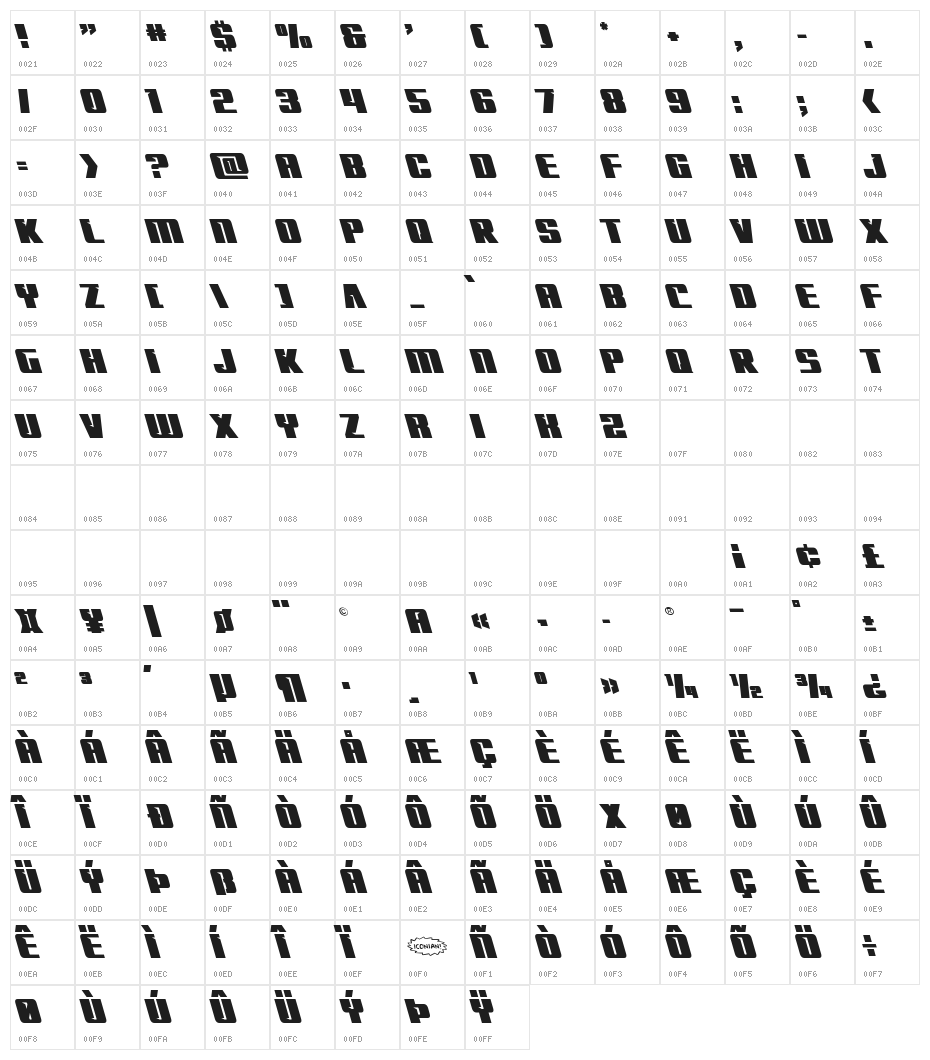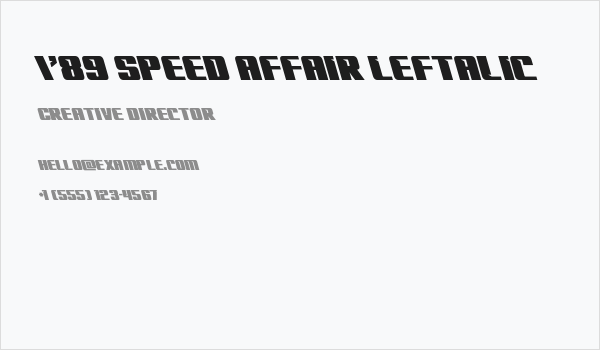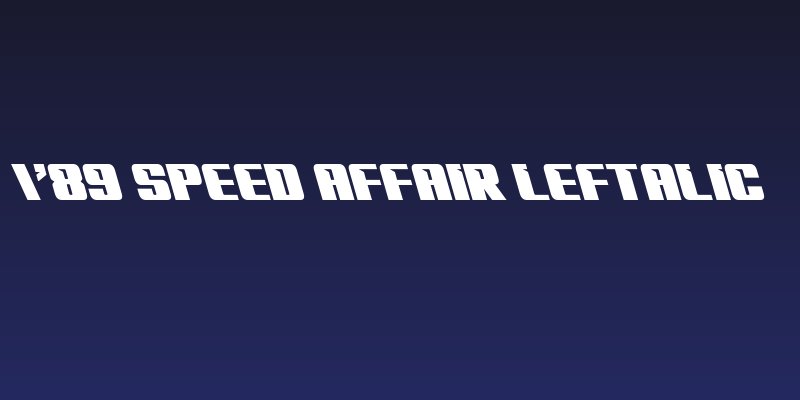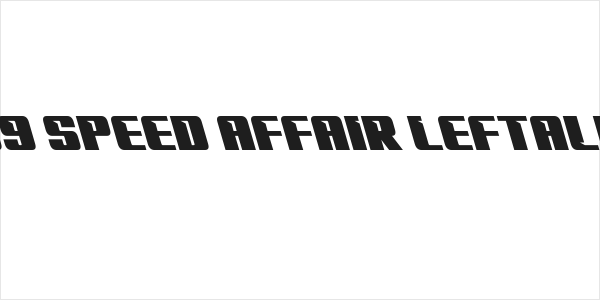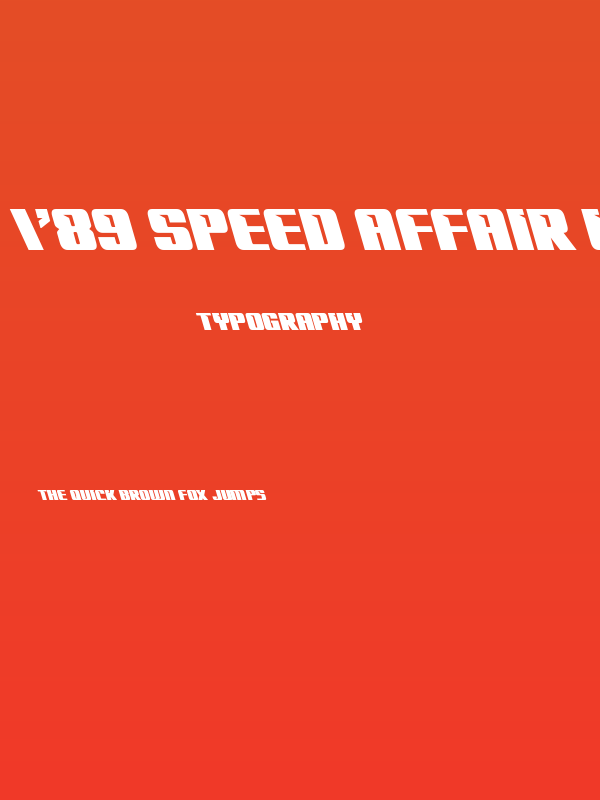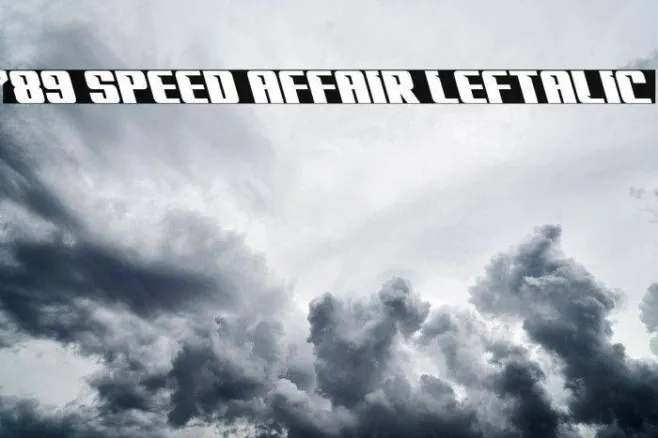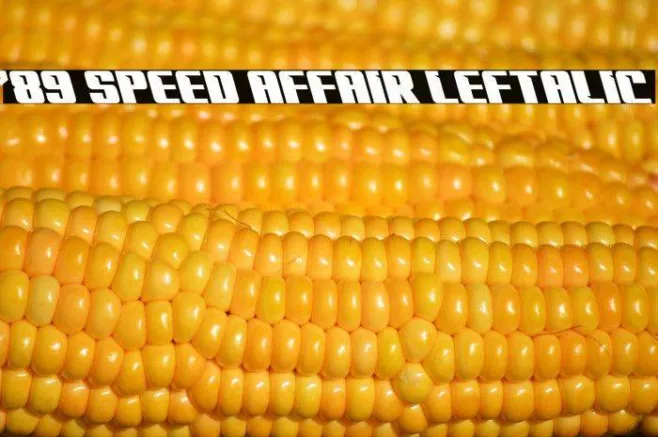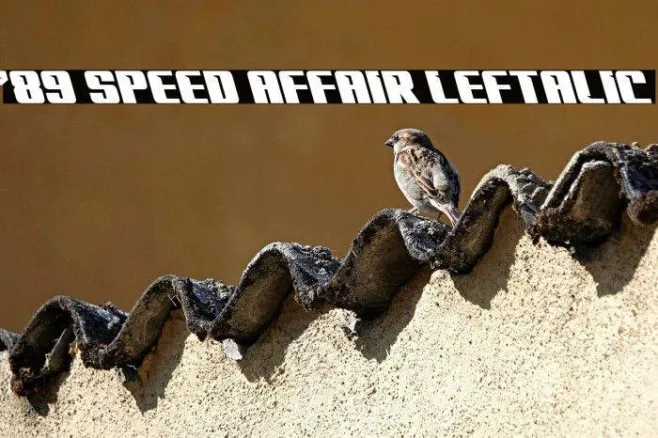
'89 Speed Affair Leftalic Font
| Projets proposés | Ideal for sports branding, automotive designs, video game titles, and any project needing a modern, energetic aesthetic. |